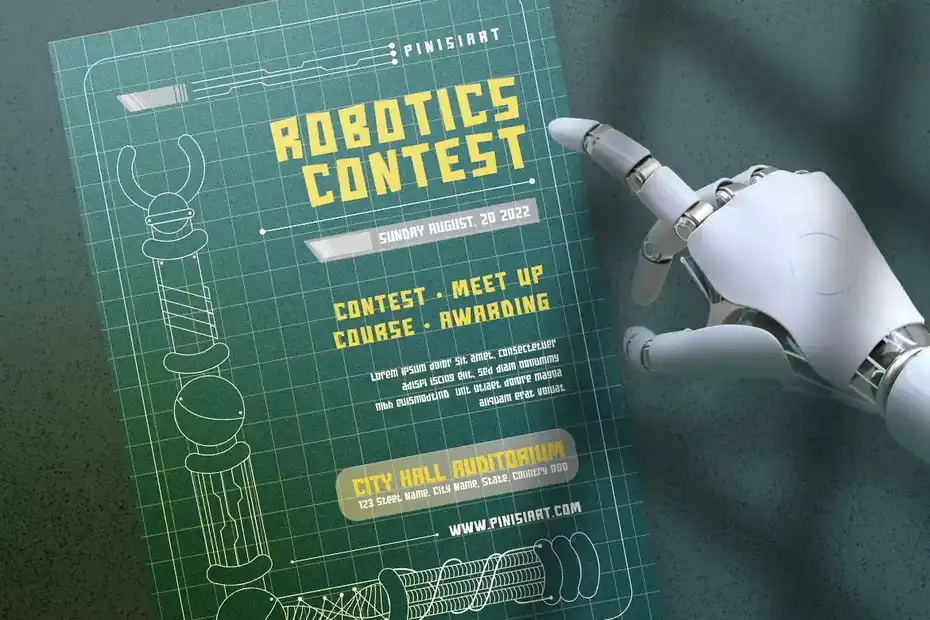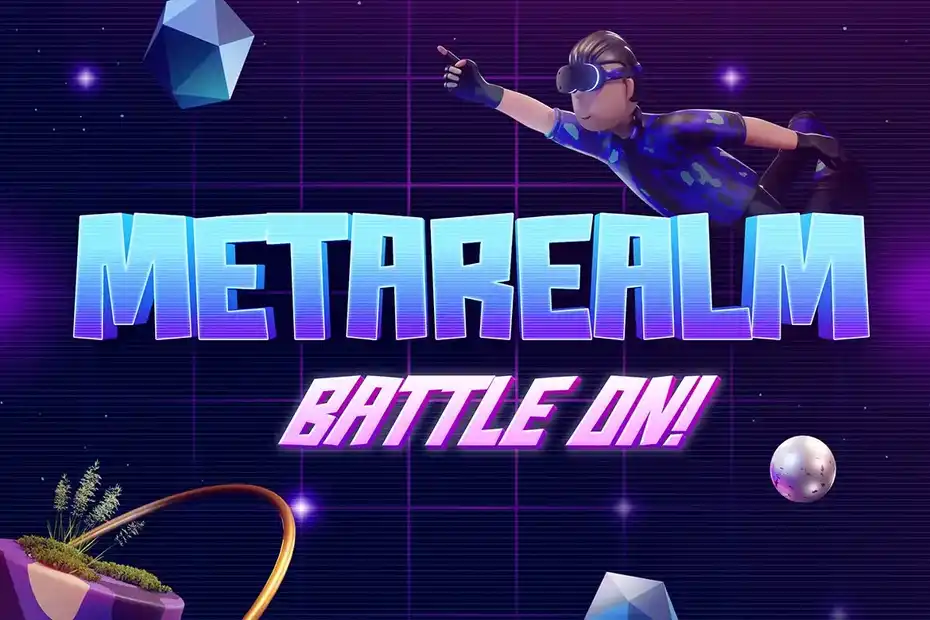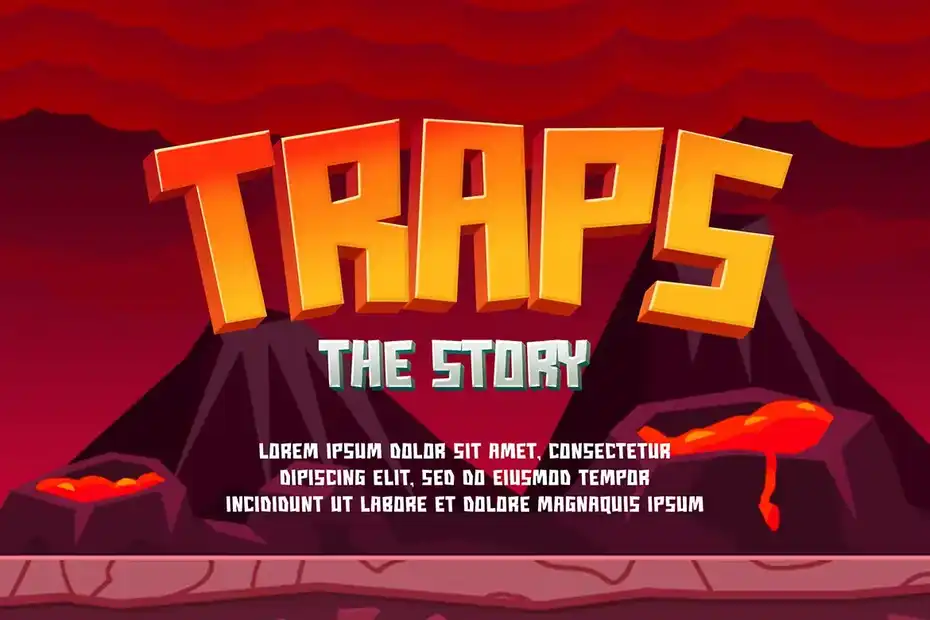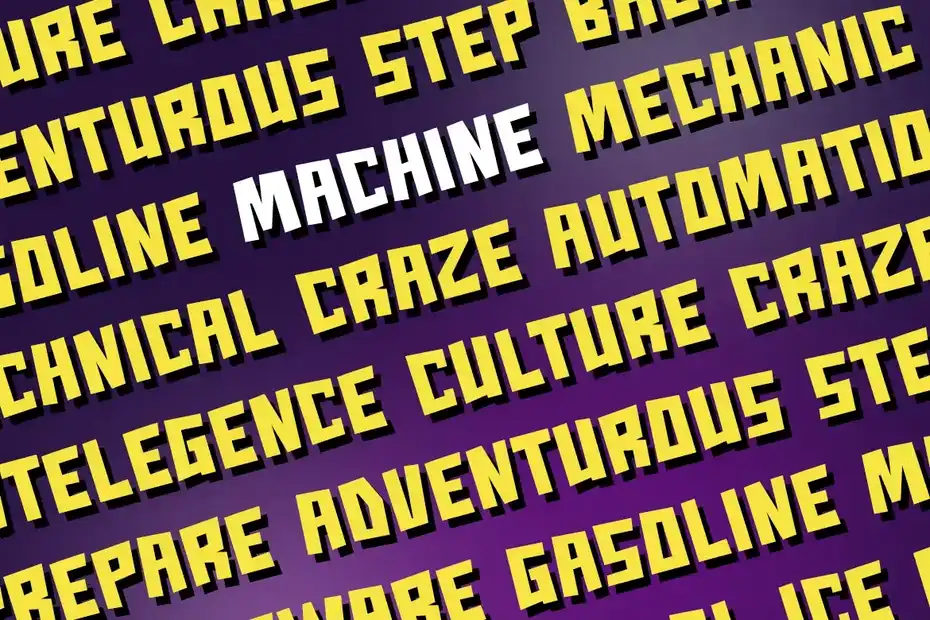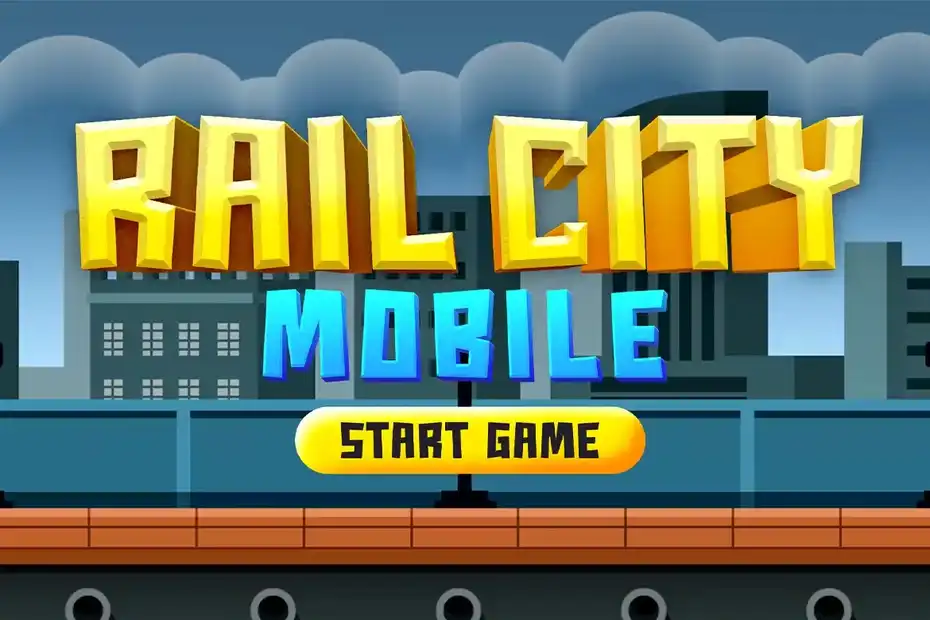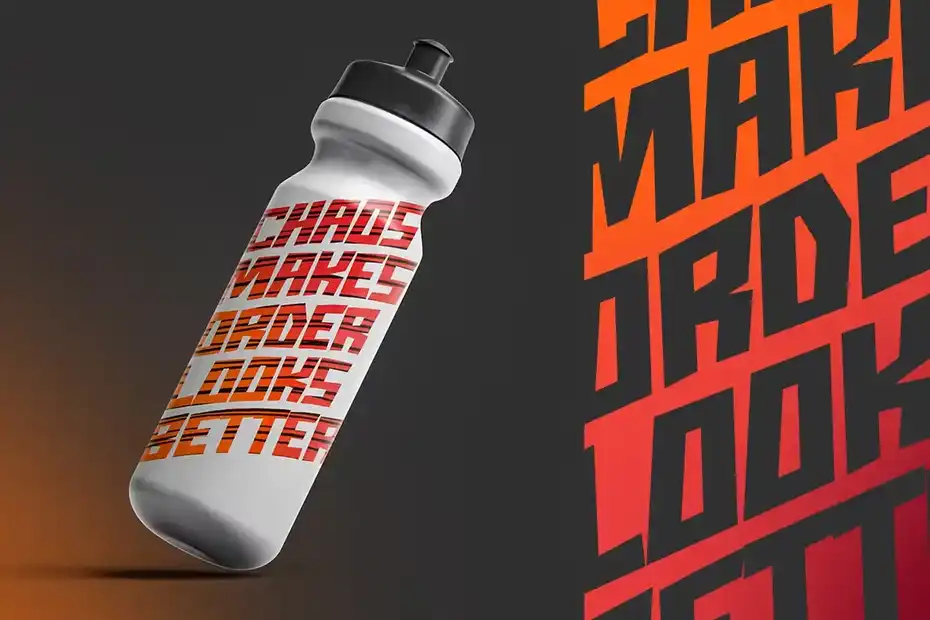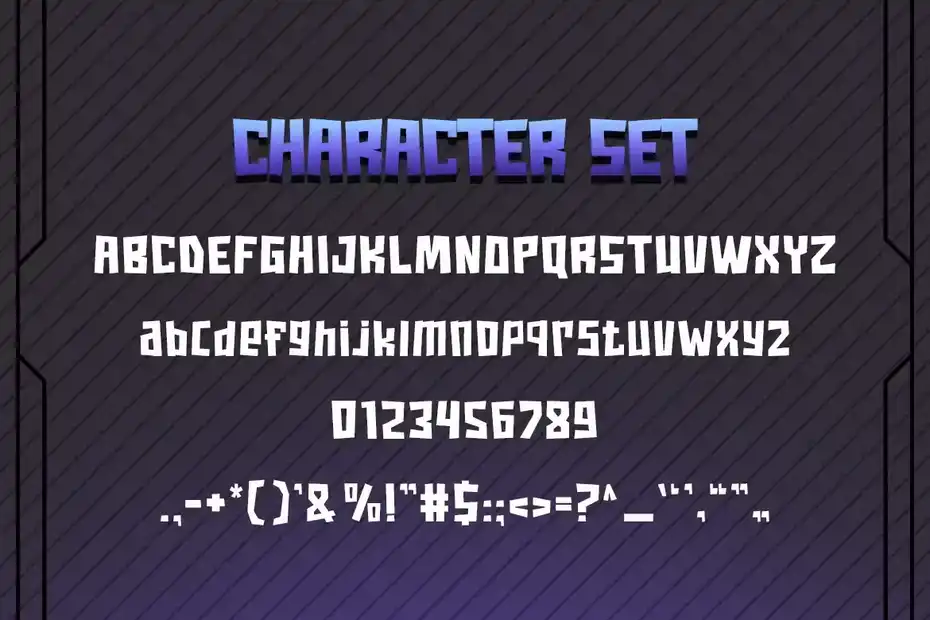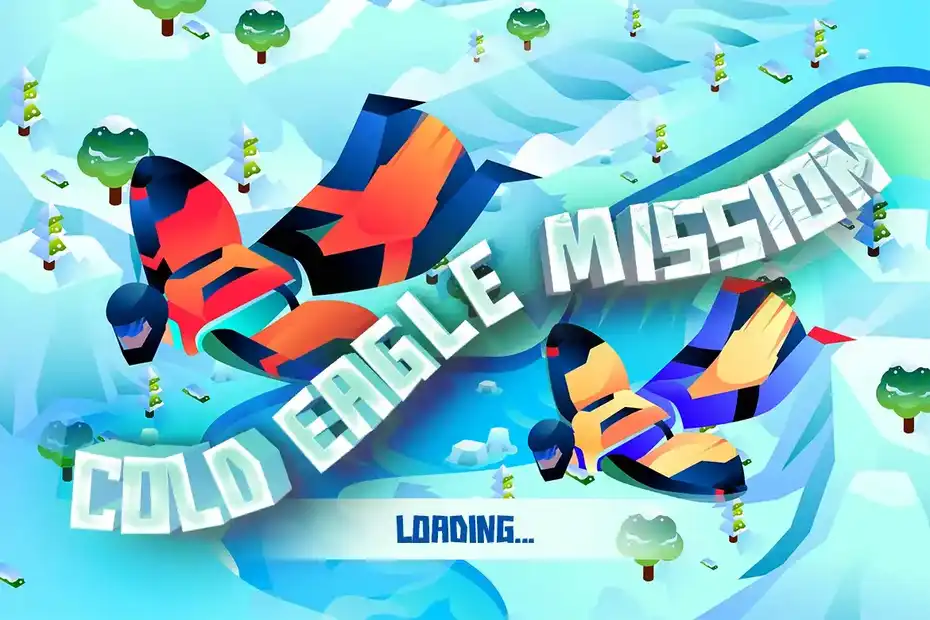
فونت انگلیسی گیمینگ Good Game – Gaming Kids Font : این فونت انگلیسی برای بازی های آنلاین، لوازم مدرسه، پوستر، کارت دعوت تولد، کاور یوتیوب، کاور شبکه های اجتماعی و غیره مناسب میباشد.
- سبک: Sans-Serif
- فضا بین حروف: معمولی
- اندازه بهینه: بزرگ (نمایش / پوستر)